可爱的文案就要配上可爱的字体,今天给大家分享的是可爱的手写创意字体
第一款手写字体:上首趣泡手写体
作为一款手写体,将我们日常手书所呈现出的形态表现得尤为突出,在此同时我们又增添出这款字的独有特点,圆圈如气泡融入到文字中,文字线条随性无所拘束,大小高低错落,给人自由、舒适、惬意、童真的强烈感受,别有一番趣味。
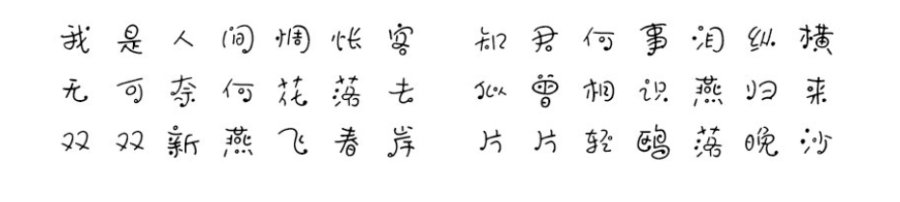
第二款:白云要吃糖
白云要吃糖设计出极贴近白云主题的笔画部件,时而敦厚可爱,时而纤细轻巧,别具一格。宽松的中宫,中偏下的重心,加上活泼俏皮的字形,使得该字具有良好的视觉体验。
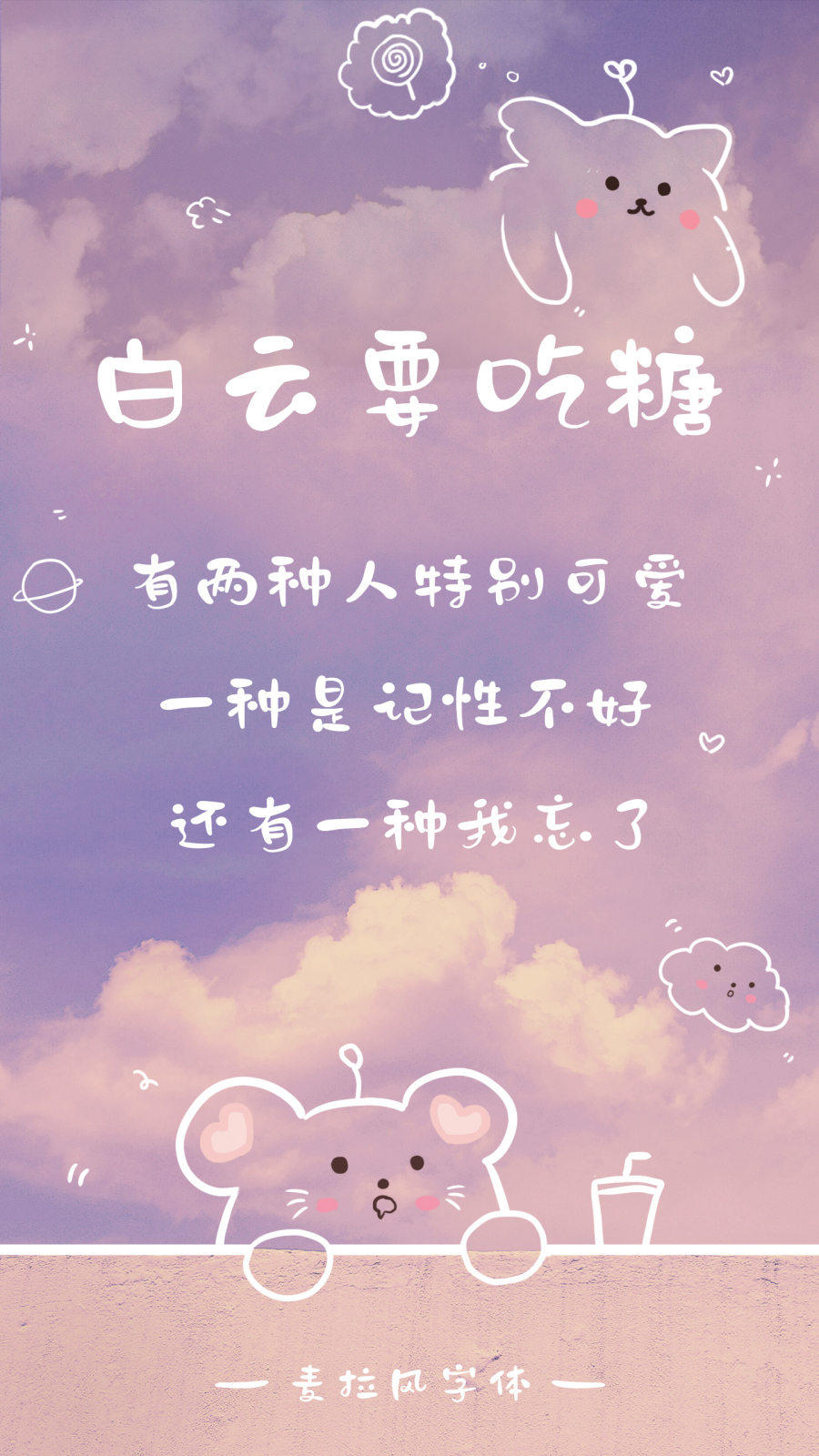
第三款:字语文墨体
字语文墨体是字语字库推出的一款非常可爱的手写艺术字体,该字体笔画粗细不一,却又极具个性,具有很好的视觉感,适合应用于艺术设计、平面宣传设计、网页设计、书法字帖等领域。